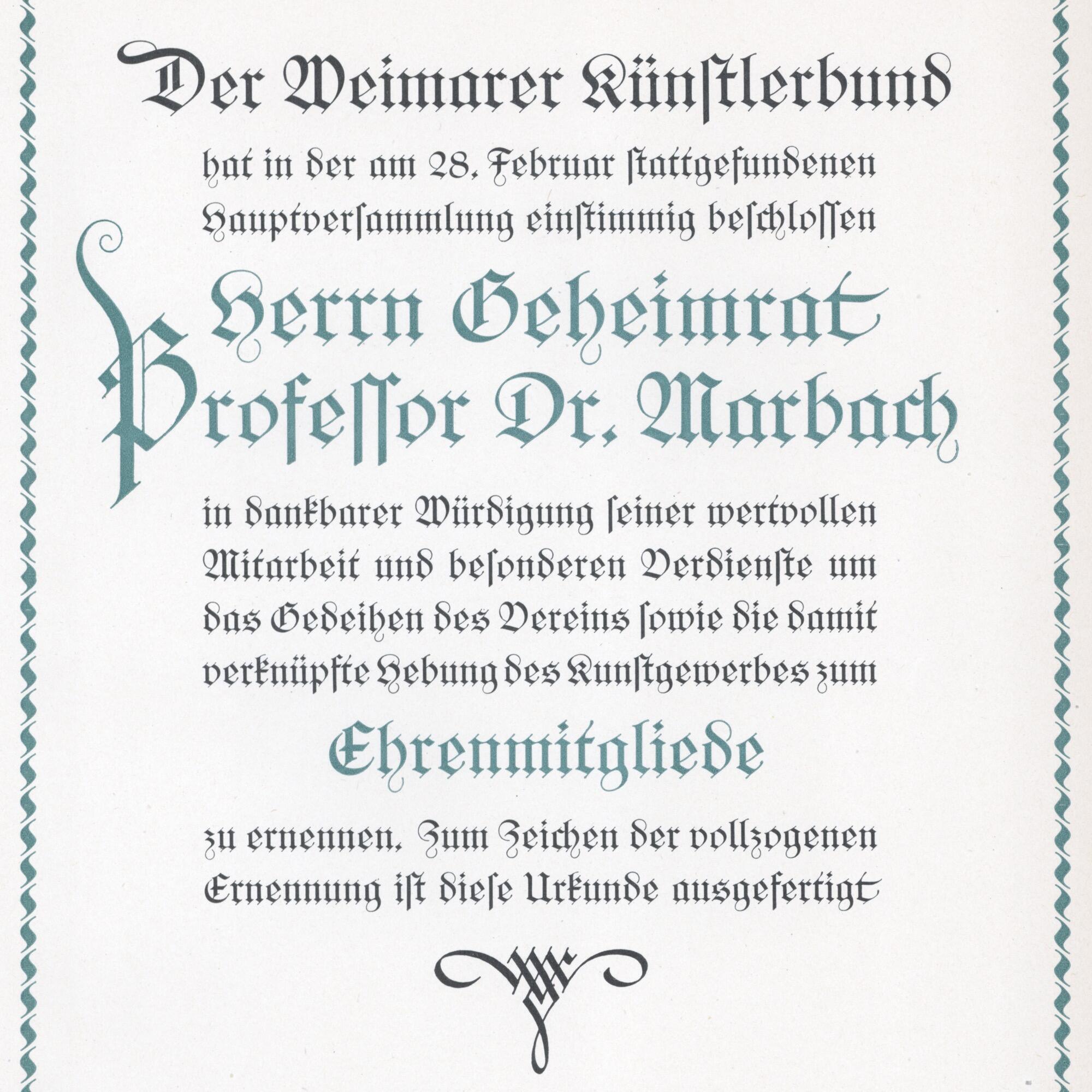
Die Waltraute wurde von Julius Edmund Robert Nitsche entworfen und erschien 1916 bei der Schriftgießerei Julius Klinkhardt. Nach der Übernahme der Gießerei war die Schrift später bei der H. Berthold AG im Programm. Die Schrift erschien in nur einem Schnitt von 6 bis 48 Punkt. Optional erhältlich waren Zierbuchstaben.
Eine Digitalisierung erschien 2019 unter dem Namen Pavillon Gotisch.